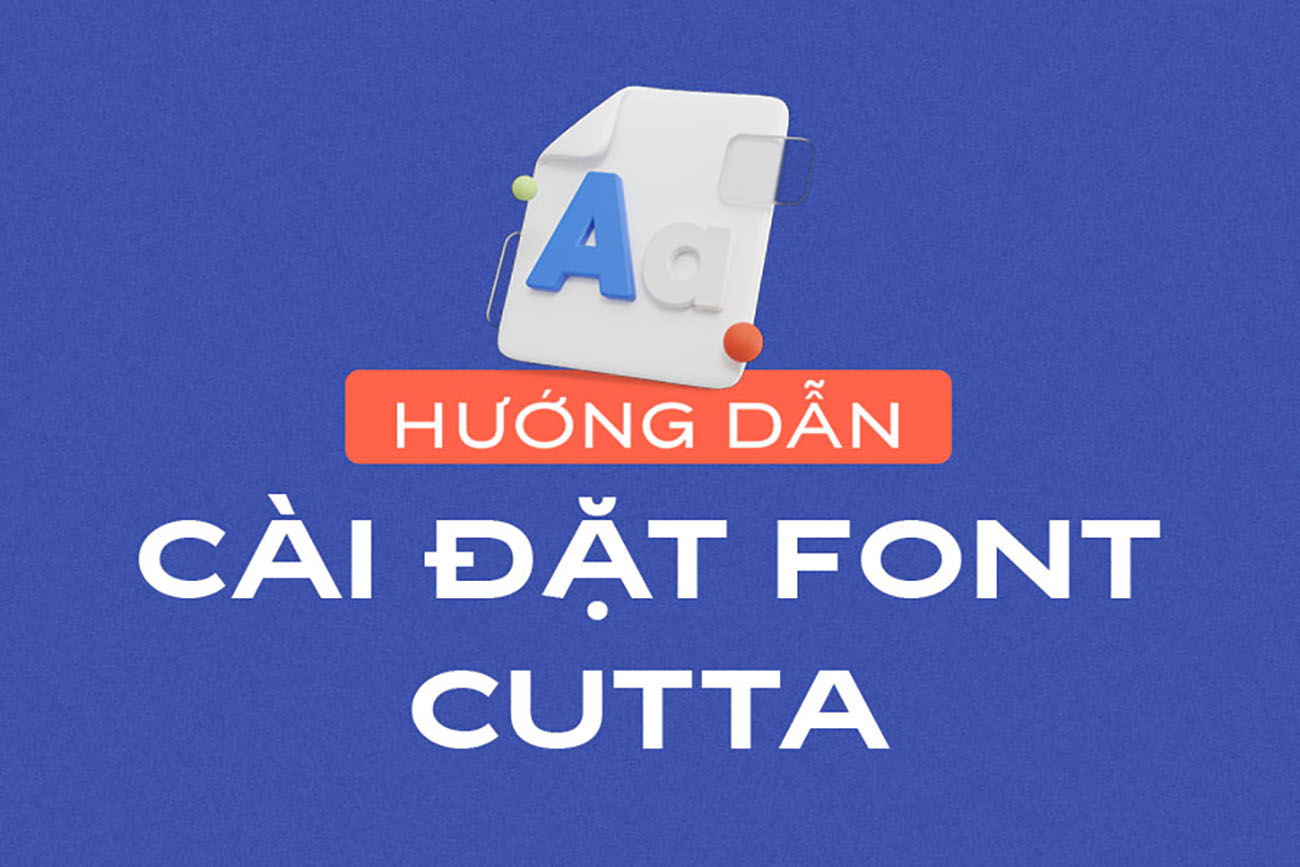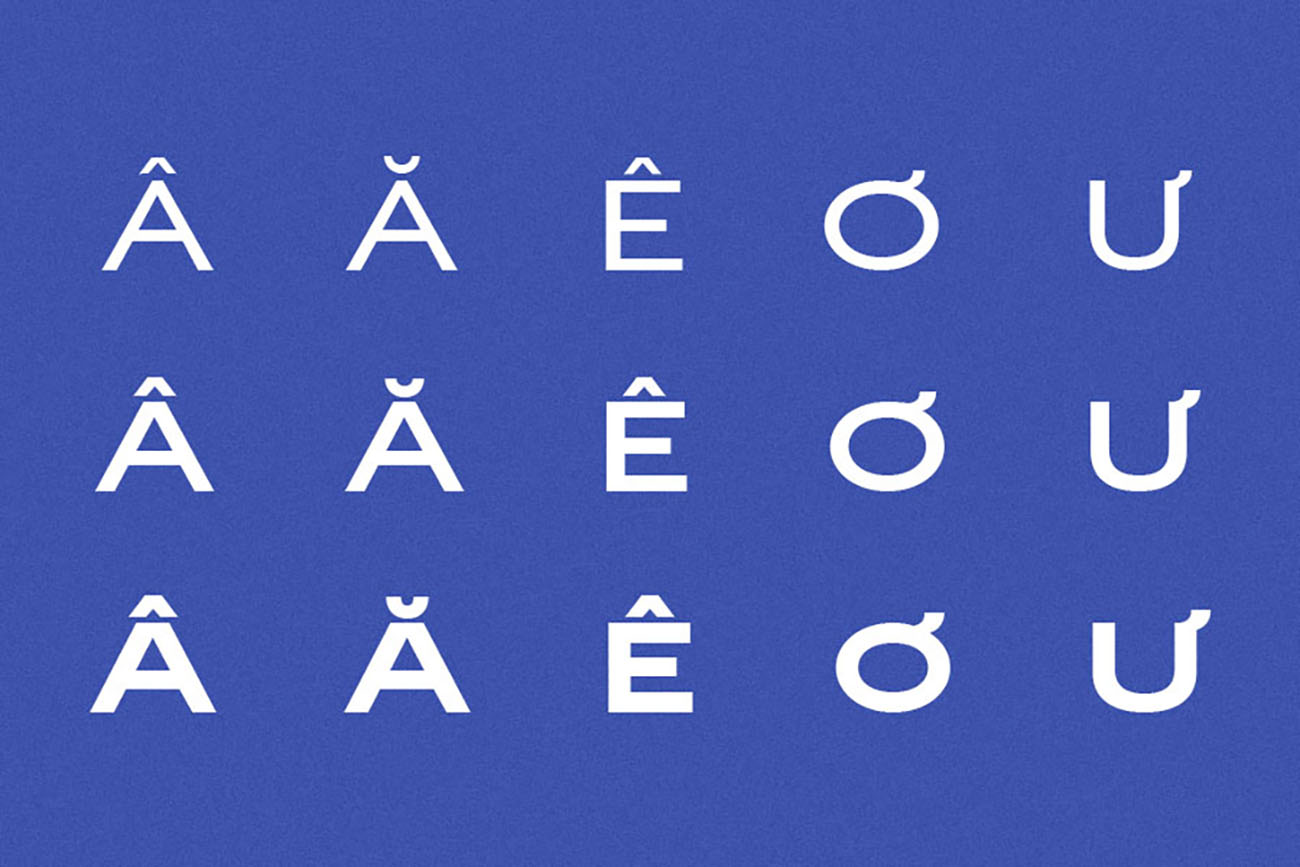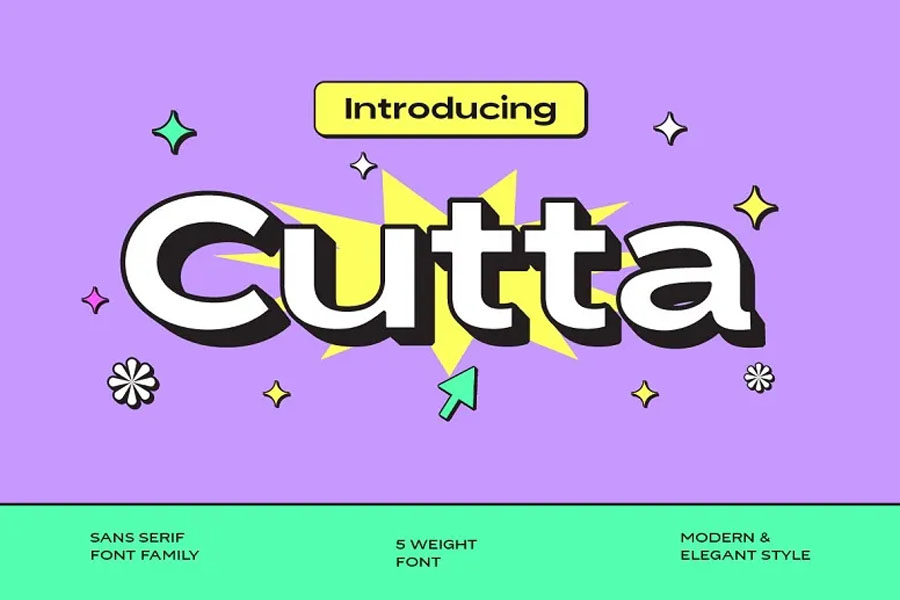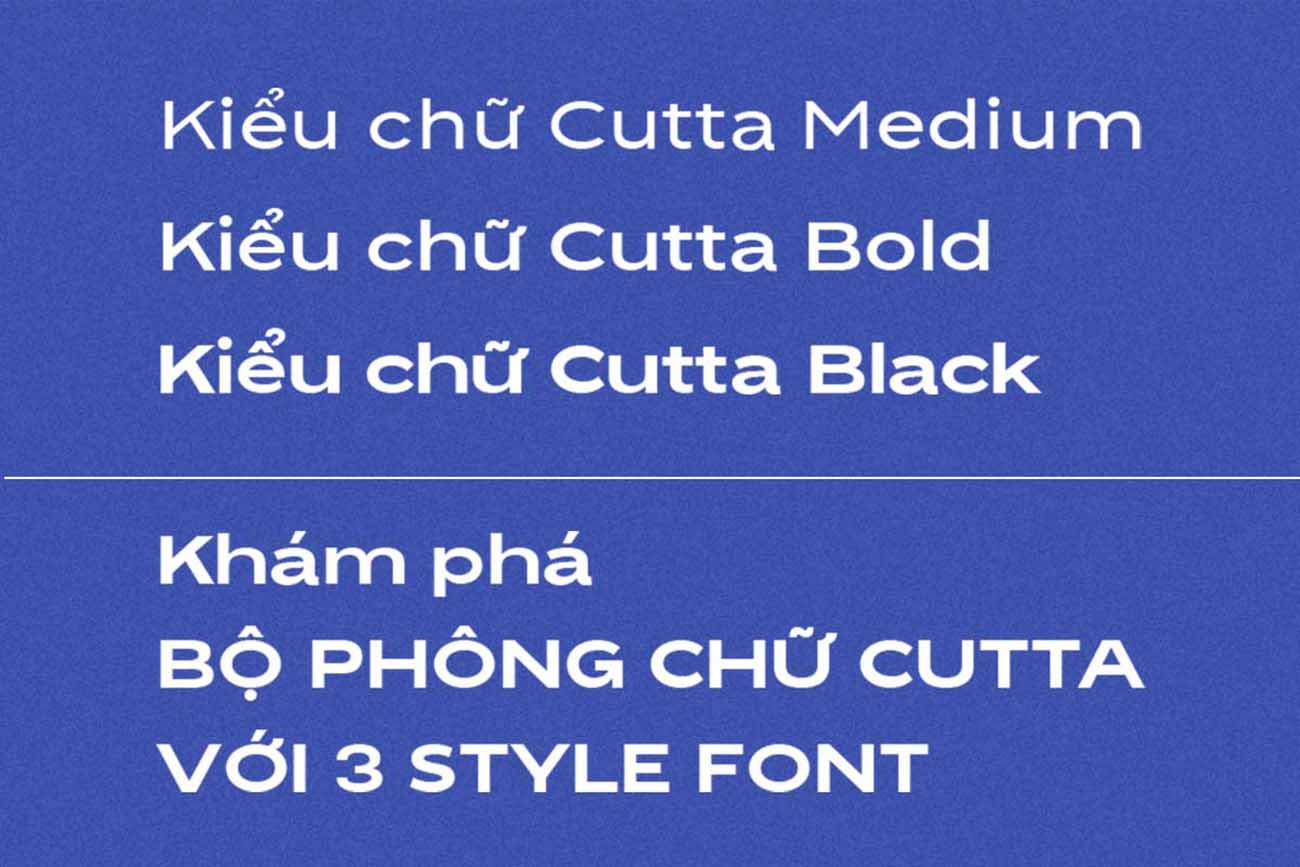
Trong thế giới thiết kế ngày nay, việc lựa chọn một font chữ đẹp, dễ đọc và đa năng luôn là bài toán quan trọng đối với designer. Nếu bạn đang tìm kiếm một kiểu chữ sans-serif hiện đại, tối giản nhưng vẫn đủ cá tính để tạo dấu ấn thương hiệu, thì font chữ Cutta chắc chắn là lựa chọn không thể bỏ qua. Với thiết kế hình học gọn gàng, đường nét sắc sảo và hỗ trợ tiếng Việt tốt, Cutta đang dần trở thành một trong những font sans-serif được yêu thích nhất năm 2025.
Font chữ Cutta là gì?
Cutta là một kiểu font chữ sans-serif hiện đại được thiết kế bởi Yukita Creative – một studio nổi tiếng với nhiều bộ font mang tính ứng dụng cao. Font mang phong cách geometric grotesque, sở hữu đường nét vuông vức, đơn giản nhưng không hề nhàm chán. Chính vì thế, Cutta dễ dàng phù hợp với các thiết kế cần sự chỉn chu, chuyên nghiệp như giao diện website, logo thương hiệu, bìa sách, menu quán cafe, hoặc thiết kế UX/UI.
Điểm mạnh lớn nhất của Cutta là khả năng cân bằng giữa tính linh hoạt và tính thẩm mỹ – không quá cá tính để khó dùng, nhưng vẫn đủ nổi bật để tạo điểm nhấn cho thiết kế.
Đặc điểm nổi bật của font Cutta
1. Phong cách geometric sans-serif hiện đại
Cutta được thiết kế theo phong cách geometric, với tỉ lệ chữ chuẩn, khoảng cách chữ hợp lý, các cạnh bo tròn nhẹ tạo cảm giác thân thiện, dễ tiếp cận. Font này không mang hơi hướng “tech” quá nặng như một số font geometric khác, mà vẫn giữ sự trung lập để phù hợp với đa dạng thương hiệu.
2. Hệ thống font đa trọng lượng (multi-weight)
Cutta gồm nhiều mức độ đậm nhạt: từ Medium, Semi Bold, Bold đến Extra Bold và Black. Điều này giúp bạn dễ dàng ứng dụng vào cả tiêu đề, nội dung văn bản và phân tầng thông tin trong thiết kế một cách rõ ràng.
3. Hỗ trợ tiếng Việt đầy đủ
Bản Việt hóa của Cutta (được phân phối trên các nền tảng như fontdep.vn hoặc S99.vn) đã được thiết kế bổ sung dấu tiếng Việt hoàn chỉnh, đảm bảo hiển thị chính xác các ký tự như ă, â, ê, đ, ơ, ư... Font không bị lỗi khi sử dụng trong các nội dung viết bằng tiếng Việt, giúp tăng tính chuyên nghiệp cho mọi dự án.
Ưu điểm khi sử dụng font chữ Cutta
Dễ đọc, tối ưu cho cả màn hình và in ấn
Thiết kế đa năng, không kén layout
Phông chữ trẻ trung, hiện đại, không lỗi thời
Hỗ trợ hệ thống ký tự Latin mở rộng, bao gồm các ngôn ngữ châu Âu phổ biến
Tổng kết: Vì sao nên chọn font Cutta?
Nếu bạn đang cần một font sans-serif mang hơi thở hiện đại, dễ đọc, hỗ trợ tiếng Việt đầy đủ và có khả năng ứng dụng cao, thì font chữ Cutta là một lựa chọn lý tưởng. Font không chỉ đẹp về mặt thẩm mỹ mà còn rất thân thiện với người dùng – kể cả với những người mới làm quen với thiết kế.
Với kiểu dáng gọn gàng, nhiều lựa chọn độ dày và khả năng tương thích đa nền tảng, Cutta xứng đáng nằm trong thư viện font thiết kế chuyên nghiệp của bạn.